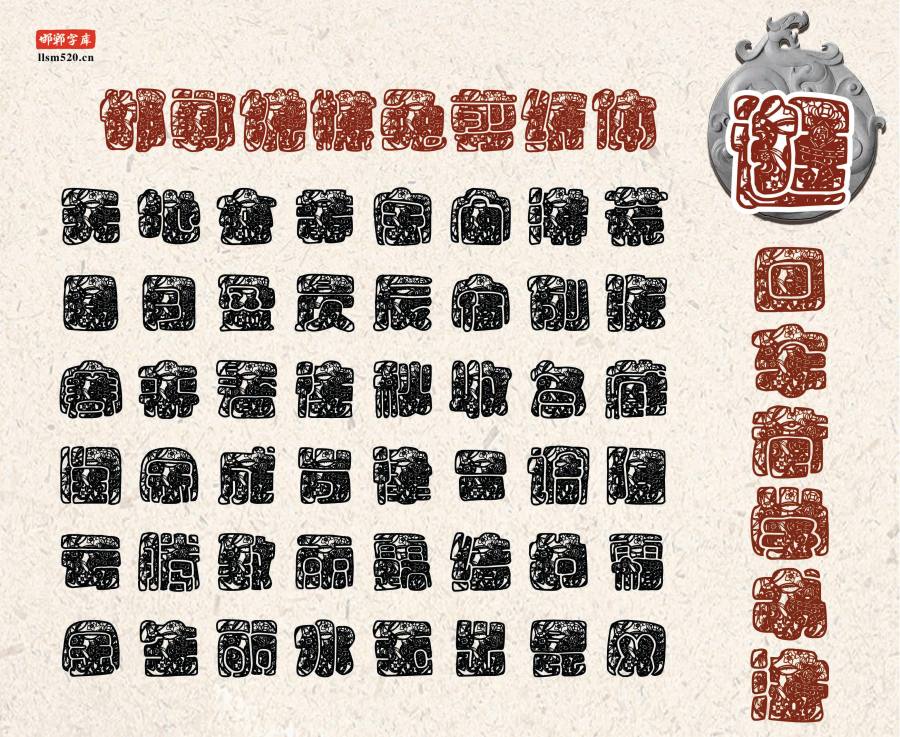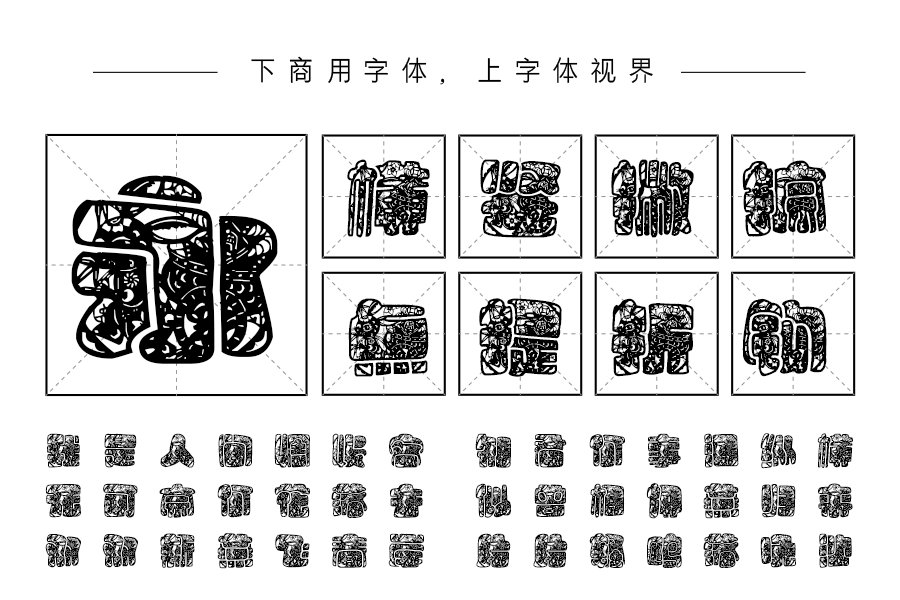
邯郸说媒兔剪纸体以韩绍杰老师创作的电脑美术字制作而成。该字体笔画粗壮,两端呈圆头,笔画相交紧密,呈凹陷窝状,中宫比较紧凑。黑字面大,字型粗旷,结构严谨,重心一致;外形采用窝窝简体,内心镶嵌说媒兔剪纸,笔划制作精良,线条刚柔相济,简洁有力。阅读舒适流畅,适用于报刊、杂志和书籍中的大型标题。
邯郸说媒兔剪纸体,笔画粗状、横竖清晰、外形采用窝窝简体,内心镶嵌说媒兔剪纸,突出醒目等特点, 有着非常强烈的现代感。
邯郸说媒兔剪纸体以韩绍杰老师创作的电脑美术字制作而成。该字体笔画粗壮,两端呈圆头,笔画相交紧密,呈凹陷窝状,中宫比较紧凑。黑字面大,字型粗旷,结构严谨,重心一致;外形采用窝窝简体,内心镶嵌说媒兔剪纸,笔划制作精良,线条刚柔相济,简洁有力。阅读舒适流畅,适用于报刊、杂志和书籍中的大型标题。
邯郸说媒兔剪纸体,笔画粗状、横竖清晰、外形采用窝窝简体,内心镶嵌说媒兔剪纸,突出醒目等特点, 有着非常强烈的现代感。